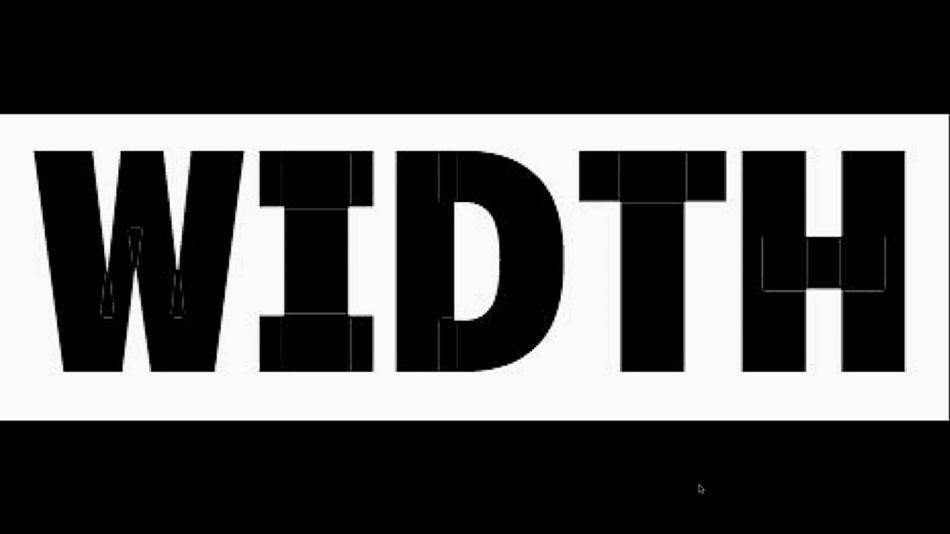
Bis zum äußersten: LucasFonts
Luc(as) de Groot
Luc(as) de Groot präsentiert schöne Schrift zwischen unschönen Extremen. Er spricht über die Nichtmachbarkeit von 32 Mastern und gibt eine Live-Demonstration seines täglichen Kampfes mit dem Grid. Er erklärt Details optischer Mathematik und gewährt damit tiefe Einblicke in das Gestalten von Buchstabenformen – und Formen generell. In seinem Vortrag behandelt er sehr logische und sehr unlogische Phänomene (die „bald“ in Buchform erscheinen werden). Luc(as) streift seine Anisotropische Topologie-abhängige Interpolationstheorie und gibt feine praktische Beispiele: bezogen auf seine ersten Schriftfamilien, und wie sie florieren. Wie begegnet man als Schriftgestalter den Herausforderungen fremder Sprachsysteme? Wie steht es um die interkulturellen Implikationen – und die praktische Anwendbarkeit? Folgen Sie Luc(as) von seinen ersten Abenteuern 1995 mit TheSans zu seinen Schriftexpeditionen heute. Es ist sehr unwahrscheinlich, dass sie dabei einschlafen.
Luc(as) de Groot
Schriftgestalter(Berlin)
Der holländische Schriftgestalter Luc(as) de Groot wurde bekannt mit seiner riesigen Schriftsippe Thesis: TheSans, TheSerif, TheMix, TheSansMono und TheAntiqua. Längst umfasst sie kyrillische, hebräische und arabische Varianten. Sein Repertoire ist noch weit größer; jede seiner Schriften bietet... Mehr lesen